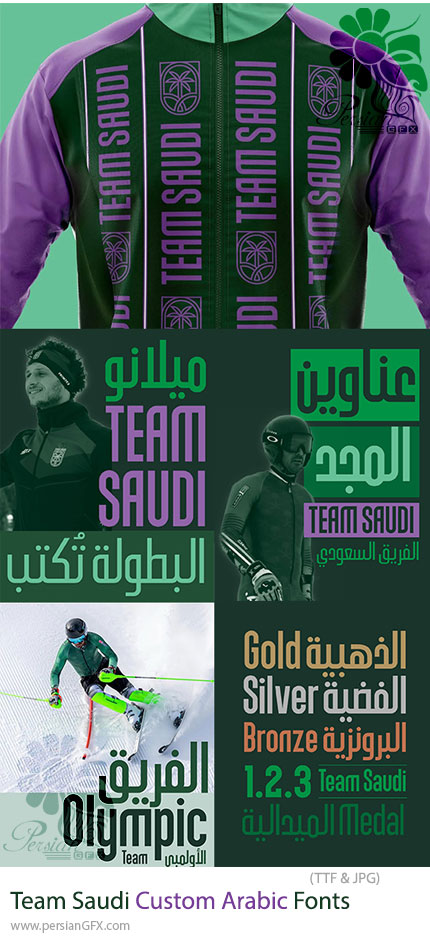
در این بخش شاهد فونتهای عربی سفارشی می باشد که با فرمت TTF بر روی سایت برای دانلود قرار گرفته است. Team Saudi Custom Arabic Fonts یک مجموعه فونت عربی اختصاصی و خلاقانه با الهام از هویت بصری، فرهنگ و روحیه ورزشی عربی است. این فونتها با طراحی مدرن و فرمهای منحصربهفرد، گزینهای مناسب برای پروژههای گرافیکی مرتبط با ورزش، برندینگ، رویدادهای ملی، پوسترها و طراحیهای تبلیغاتی هستند. این مجموعه با تمرکز بر تایپوگرافی عربی حرفهای، به طراحان امکان میدهد نوشتههایی قدرتمند، چشمگیر و هماهنگ با سبکهای مدرن ایجاد کنند. طراحی این فونتها برای نمایش انرژی، اتحاد و هویت تیمی الهام گرفته از مفهوم Team Saudi و نمایندگان رسمی عربستان در عرصههای بینالمللی ورزشی است.
ویژگیهای کلیدی فونت:
- فونت عربی سفارشی با طراحی اختصاصی
- سبک مدرن و ورزشی مناسب پروژههای ملی و برندینگ
- فرم حروف قدرتمند و قابل استفاده در تیترها
- مناسب طراحی پوستر و کمپینهای تبلیغاتی
- ترکیب زیباییشناسی عربی با ظاهر معاصر
- مناسب پروژههای دیجیتال و چاپی
- ایجاد تایپوگرافیهای خاص و حرفهای